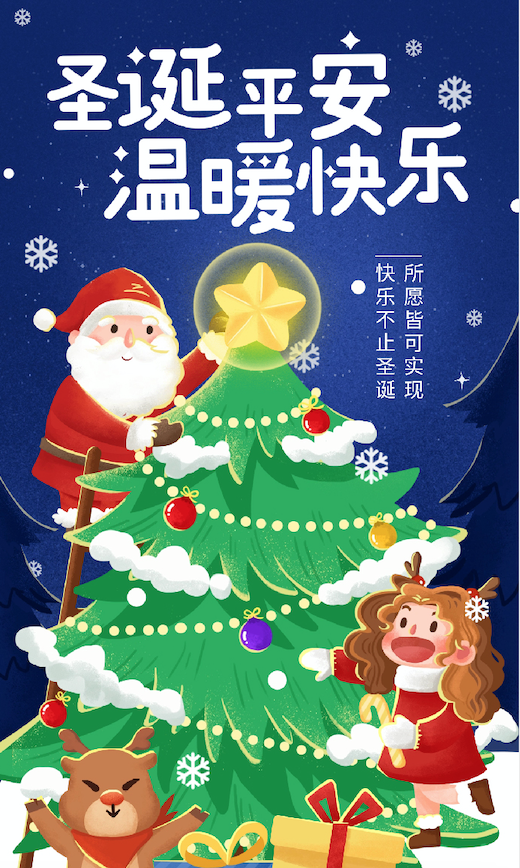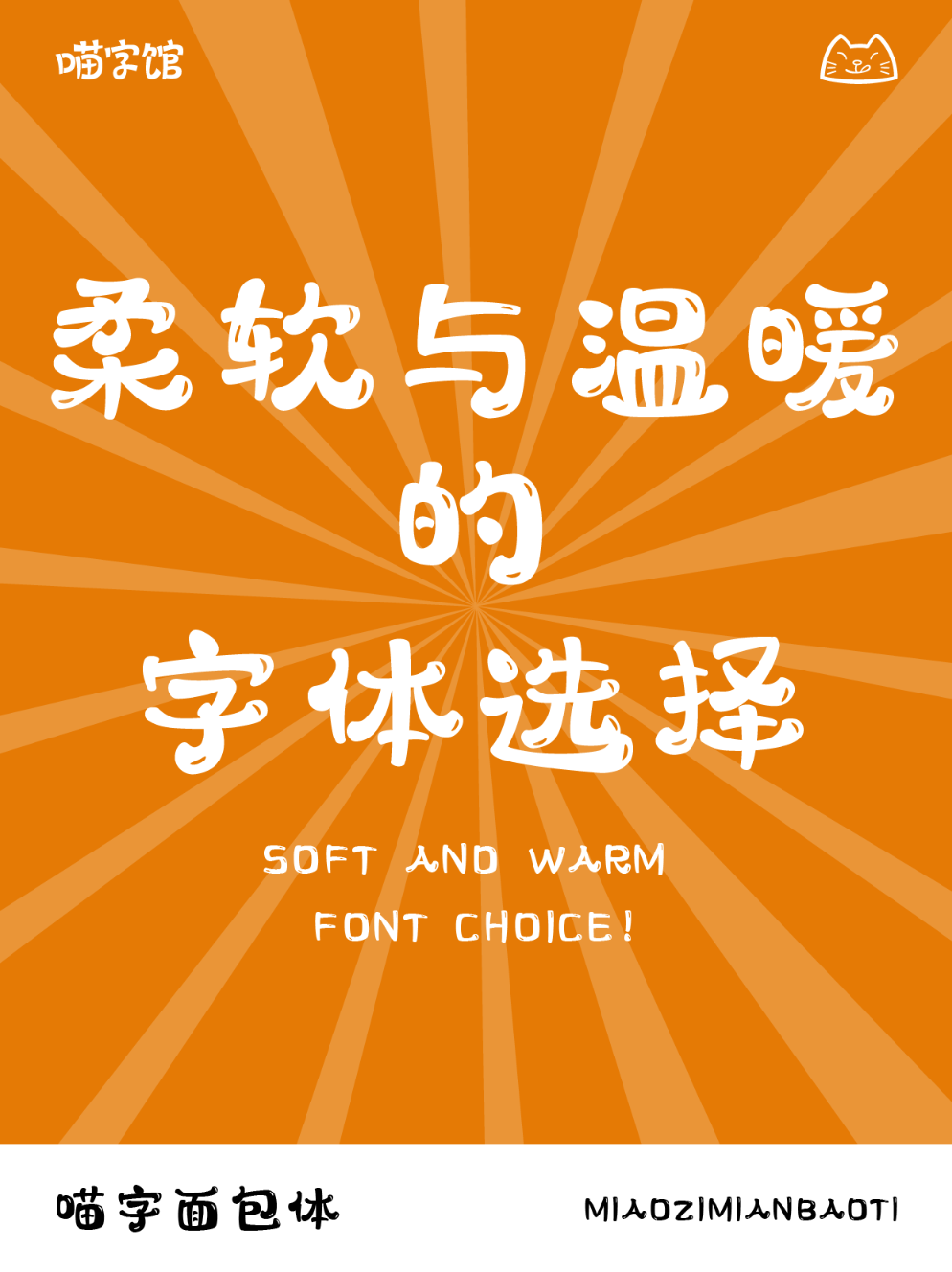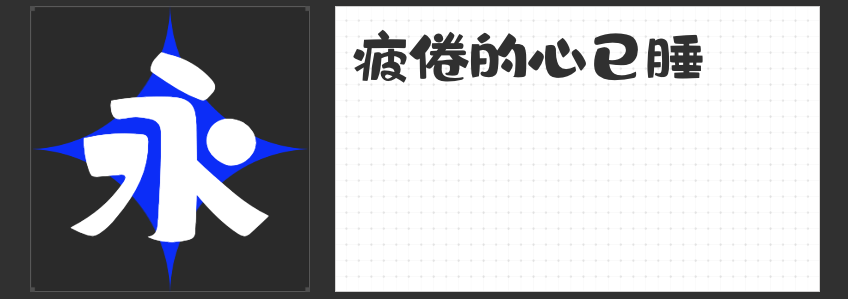
四款萌趣可爱中文字体,让你的设计瞬间萌化人心!
在追求设计独特性与视觉吸引力的今天,选择一款合适的字体往往能为作品增色不少。今天,就为大家推荐四款充满可爱风格的中文字体,它们各具特色,定能让你的设计作品更加生动有趣。
1. 高手兵克星耀体
这款字体融合了现代与复古的元素,以独特的笔触和造型展现出一种别样的可爱感。它的每一个字都仿佛是一个小小的战士,充满了力量和活力,同时又不失俏皮可爱,非常适合用于游戏、动漫或创意海报的设计中。
2. 励字憨憨简
憨态可掬,是这款字体的最大特点。它的字形圆润饱满,线条简洁流畅,给人一种温暖而亲切的感觉。无论是用于励志文案、儿童读物还是温馨广告,都能很好地传达出积极向上的氛围和满满的爱心。
3. 喵字面包体
听到名字就能想象到它的可爱模样。这款字体创造出了一种既温馨又有趣的视觉效果。它的字形圆润可爱,线条柔和流畅,非常适合用于甜品店、咖啡馆或宠物相关的设计中,让人一眼就爱上。
4. 喵字文案体
与喵字面包体相似,它的字形设计简洁明了,易于阅读,同时又不失可爱感。无论是用于社交媒体文案、产品包装还是品牌宣传,都能让你的文字更加吸引人眼球,留下深刻印象。
以上四款可爱风格的中文字体,每一款都有其独特的魅力和应用场景。选择适合自己设计风格的字体,让你的作品更加生动有趣吧!